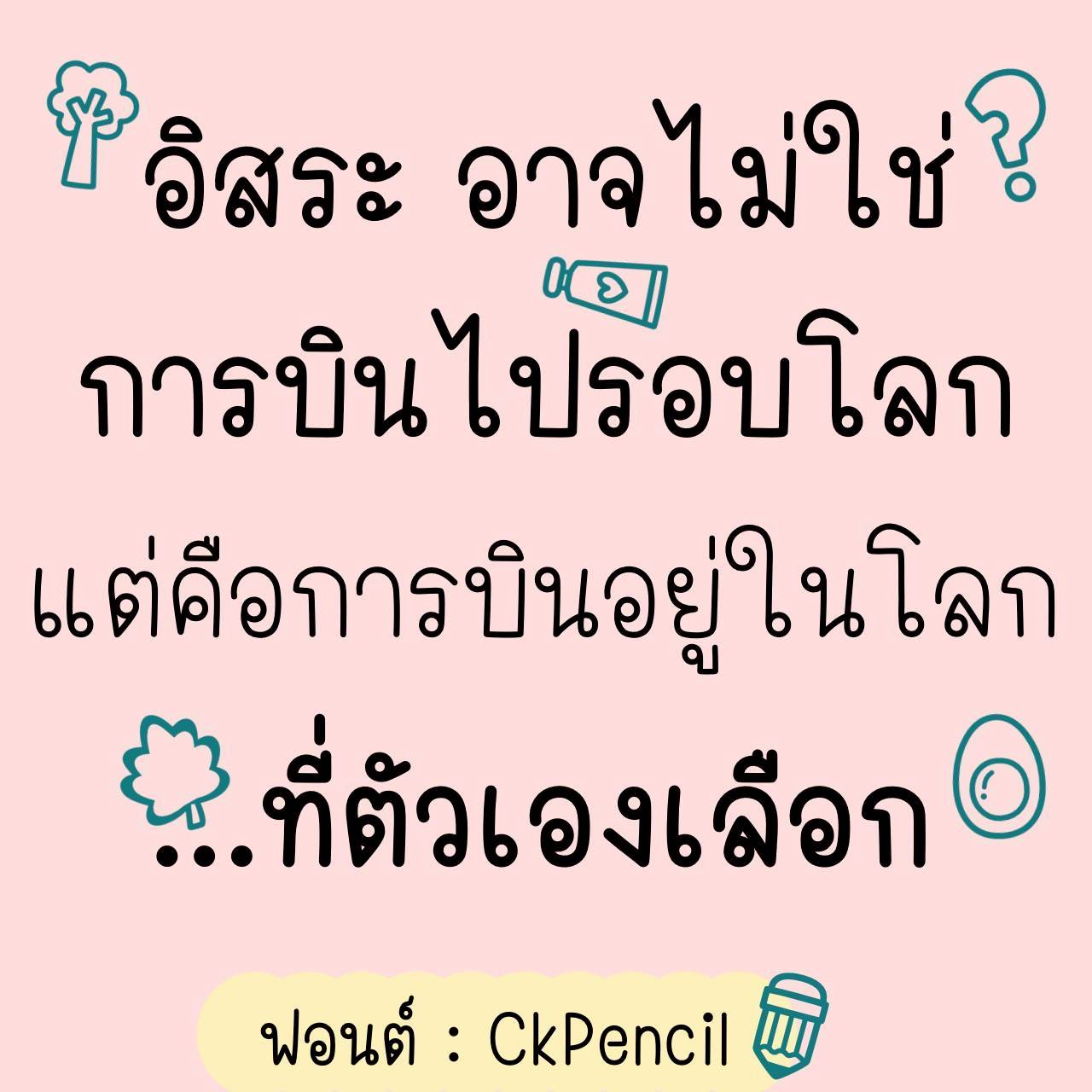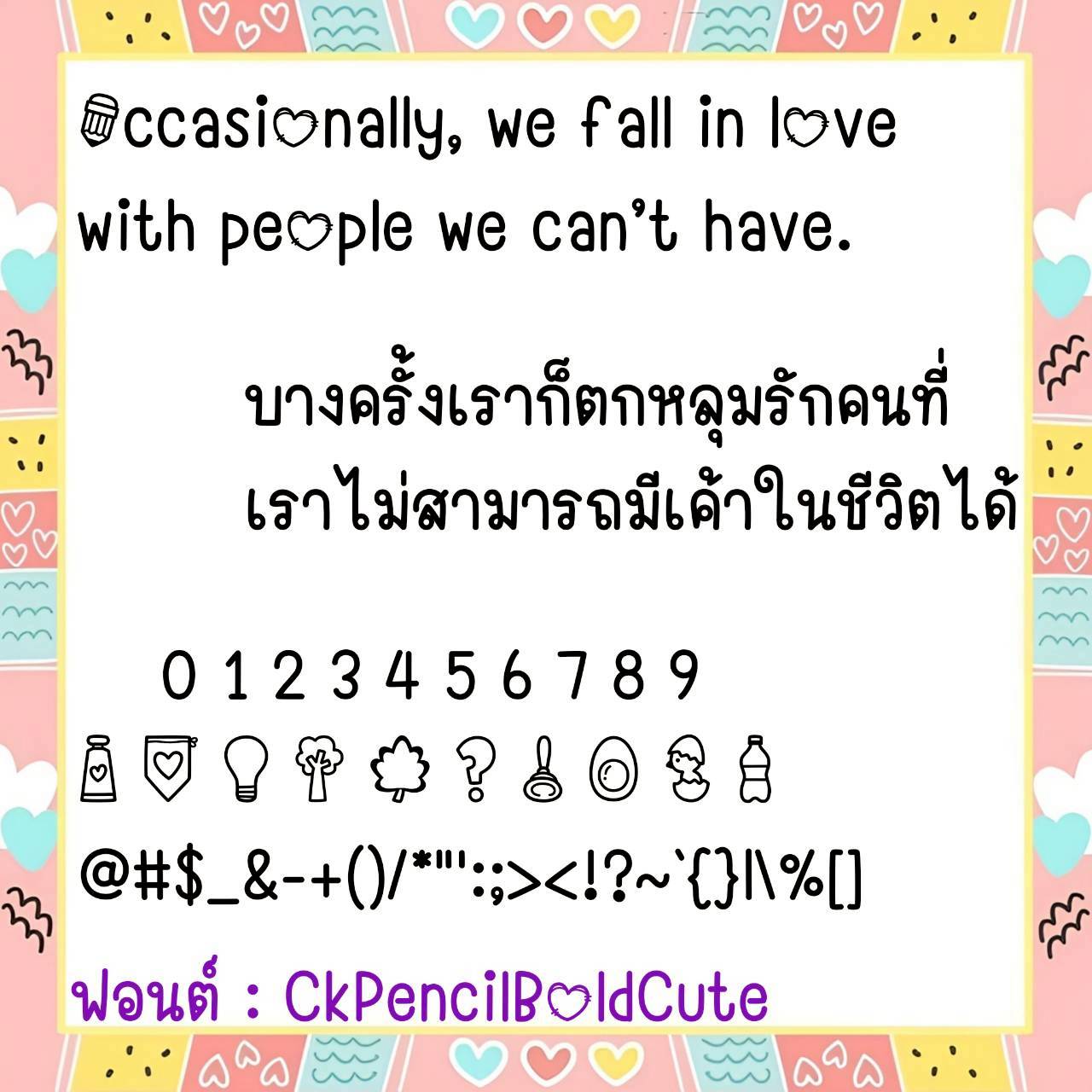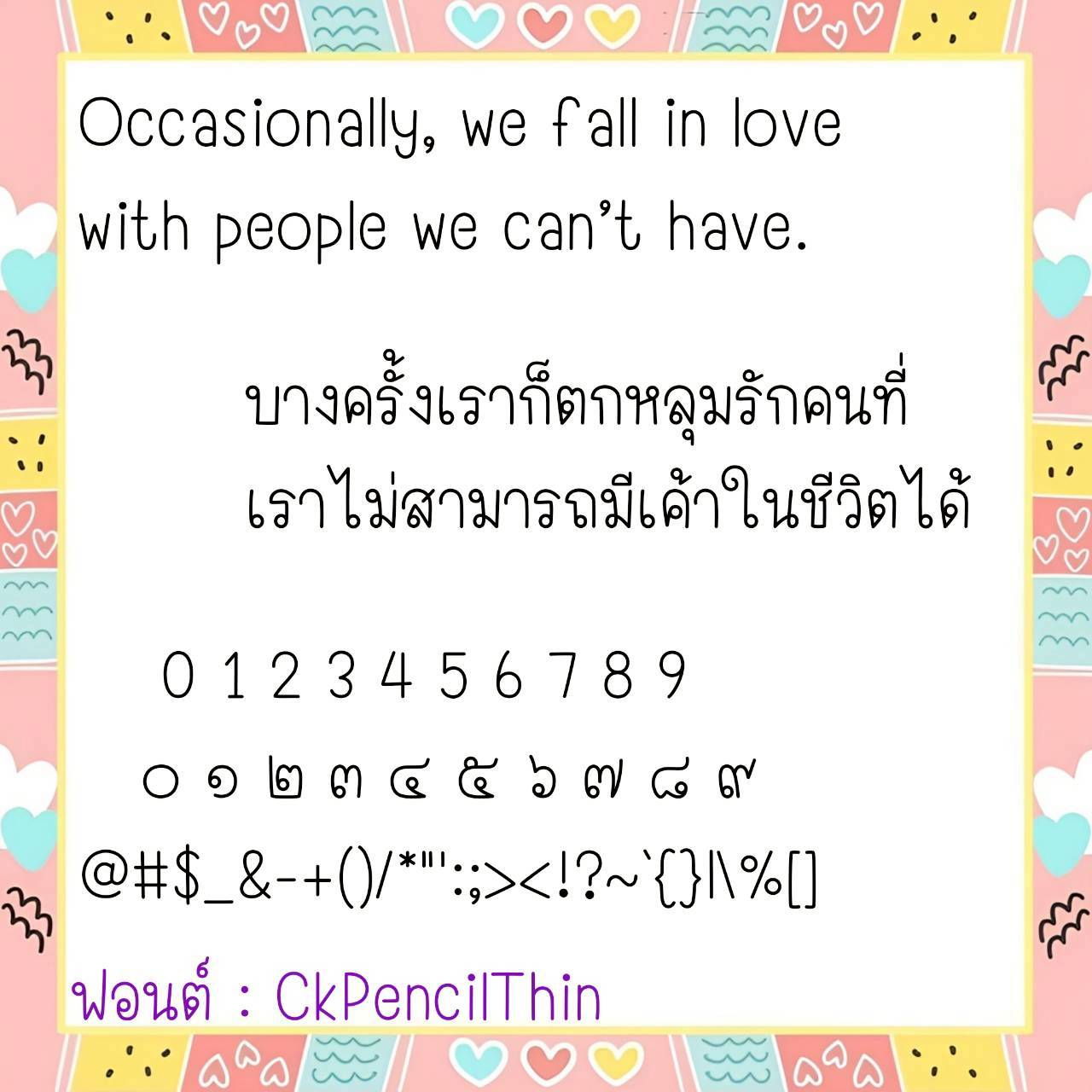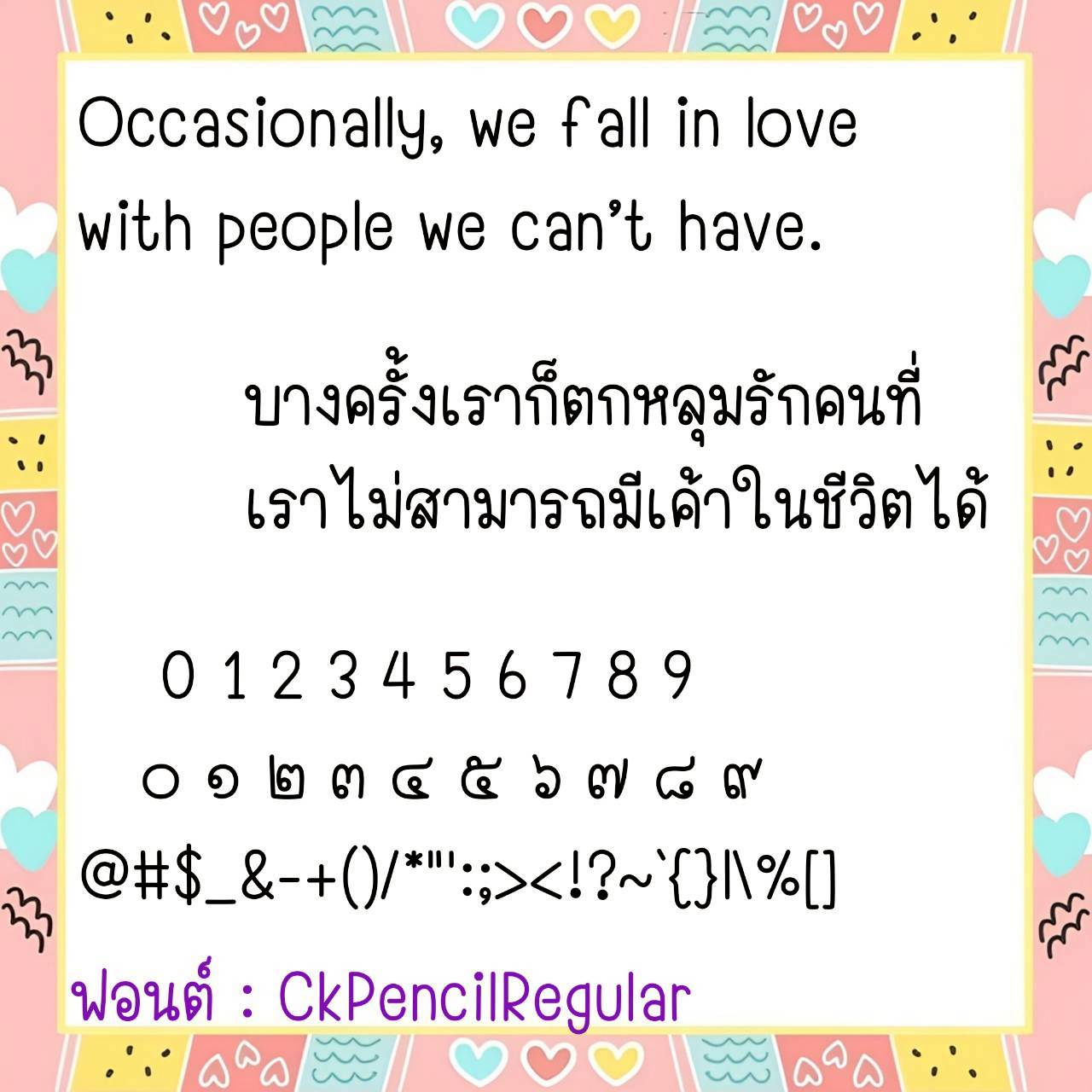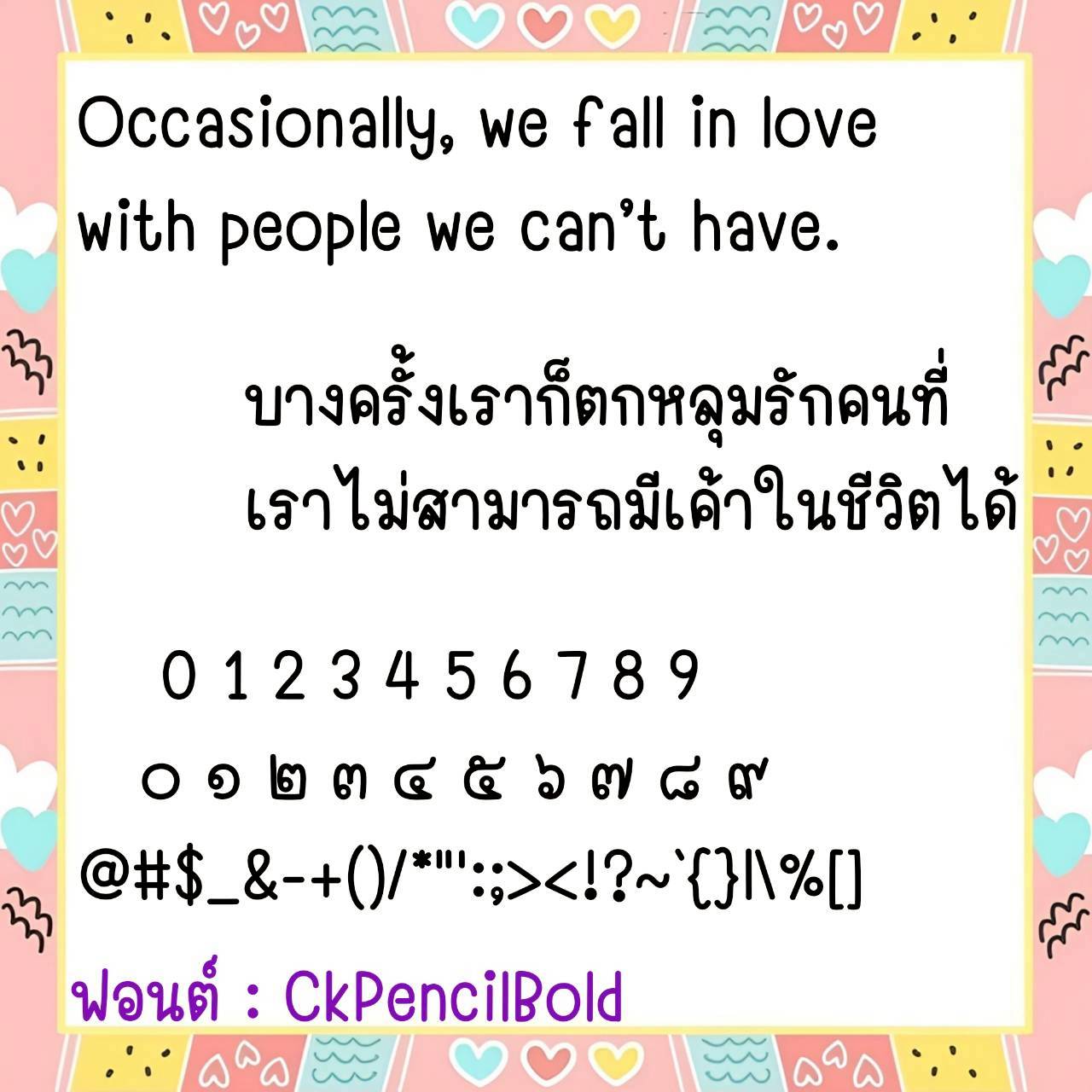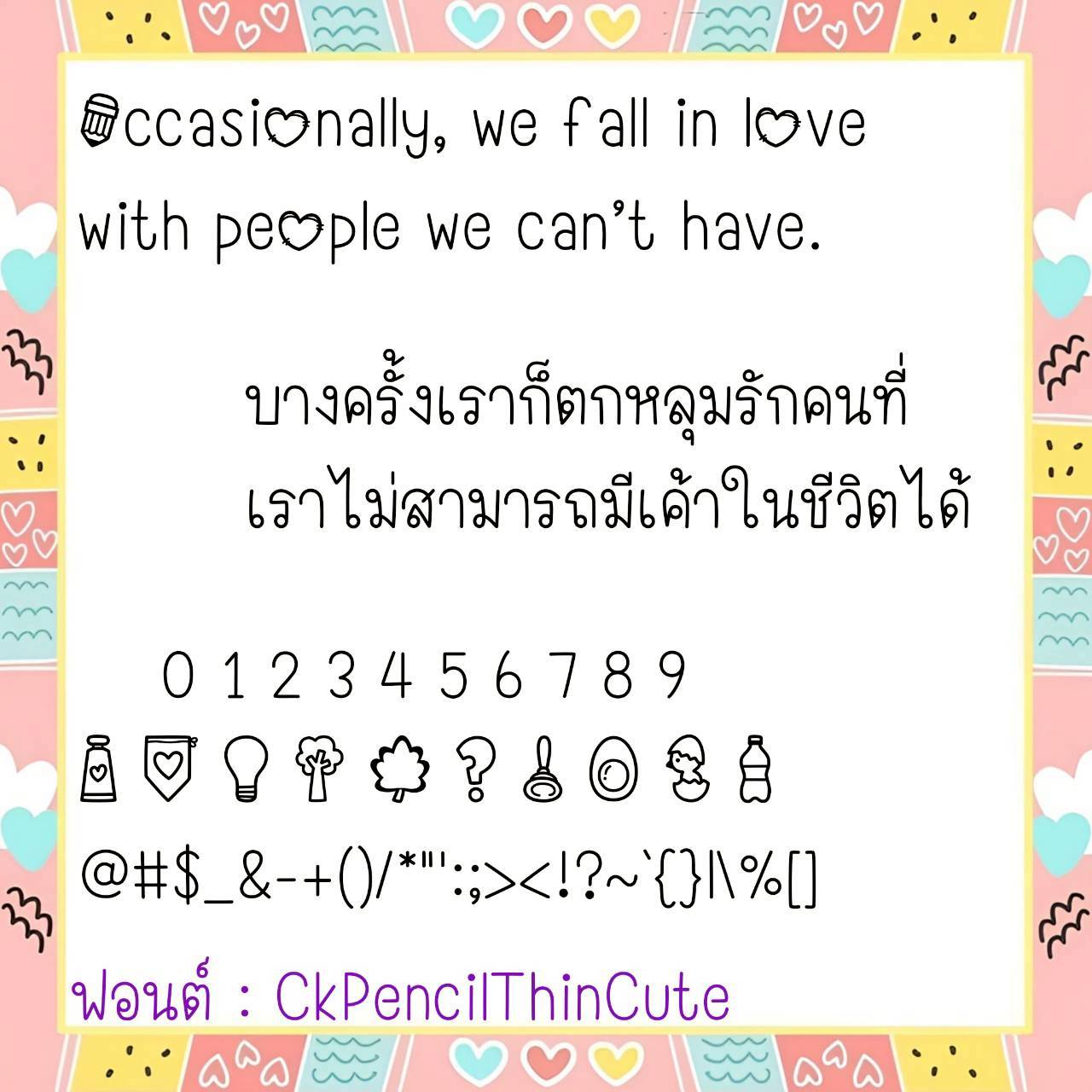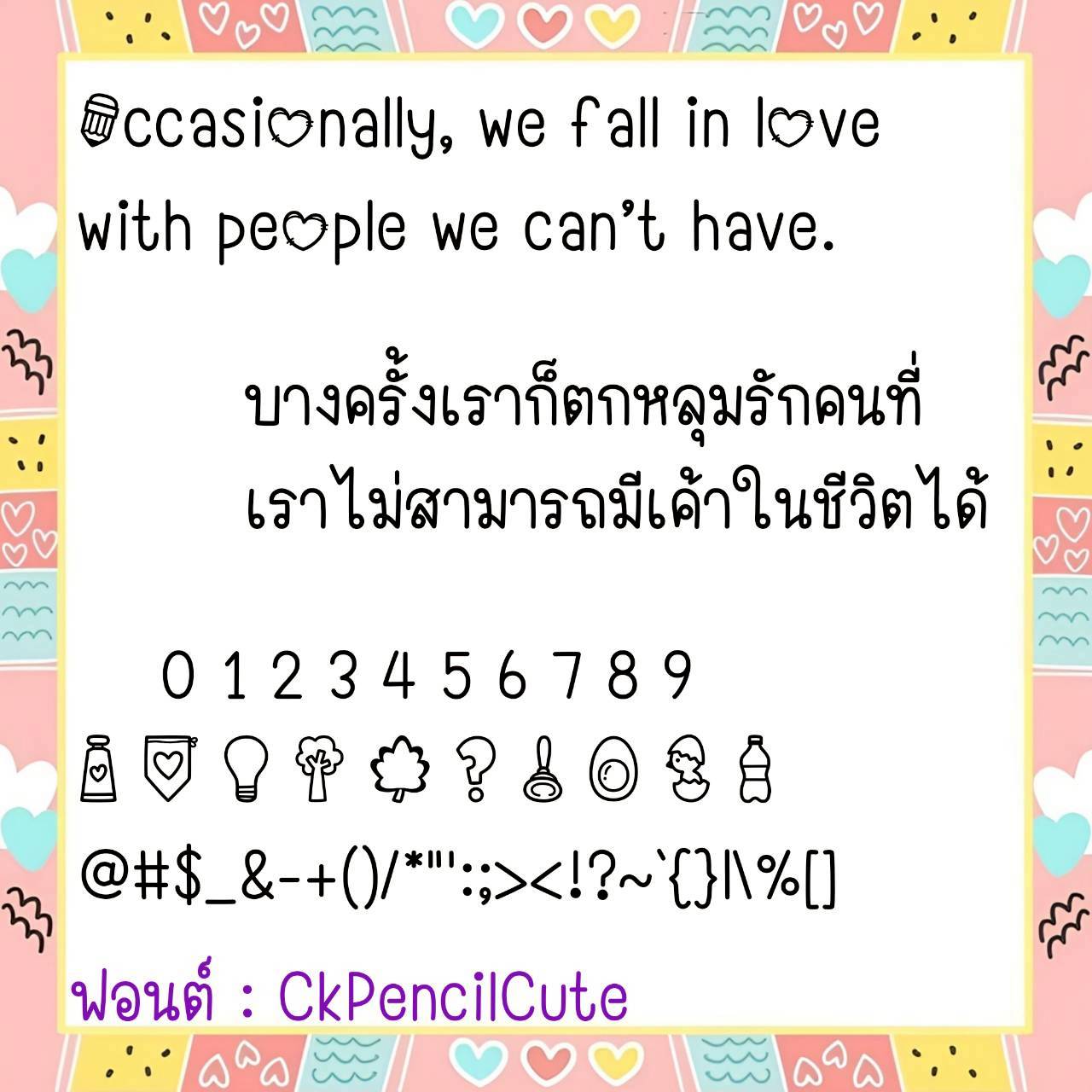
Font CkPencil
ชื่อสินค้า : Font CkPencil 💙
🔸 ฟอนต์ลายมือน่ารักๆแบบกึ่งวัยรุ่น ตัวอักษรมีความเหลี่ยมความมนปนๆกันไป แต่ยังเน้นอ่านง่ายสบายตาเช่นเดิม และยังมีไฟล์อิโมจิน่ารักๆ ที่ใช้แทนเลขไทยให้ด้วยค่ะ 🥰💙
🔹 A cute, semi-teenage handwriting font. The letters are a mix of edges and roundness, but still easy to read and comfortable to the eyes. There are also cute emoji files that can be used instead of Thai numbers. 🥰💙